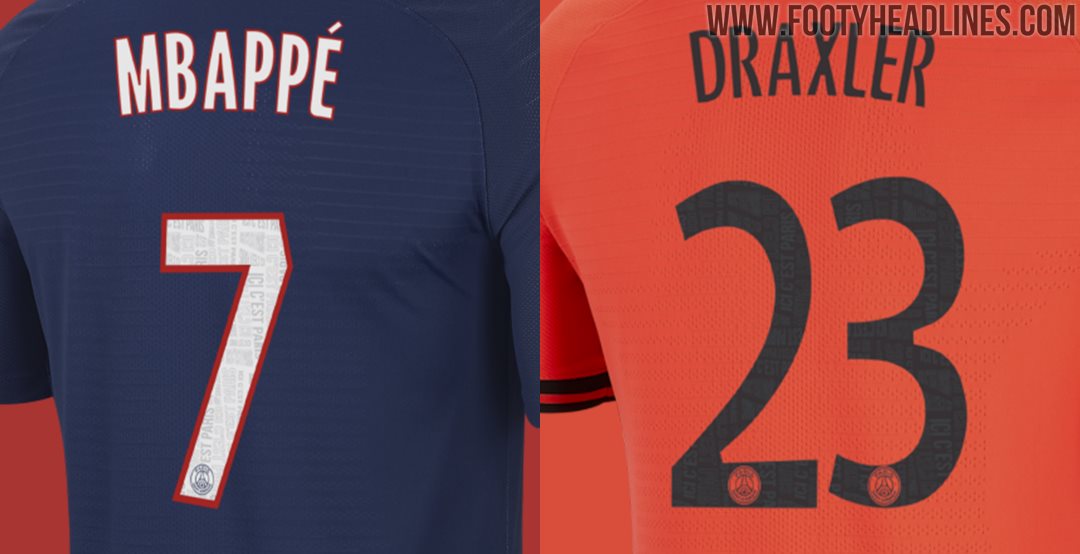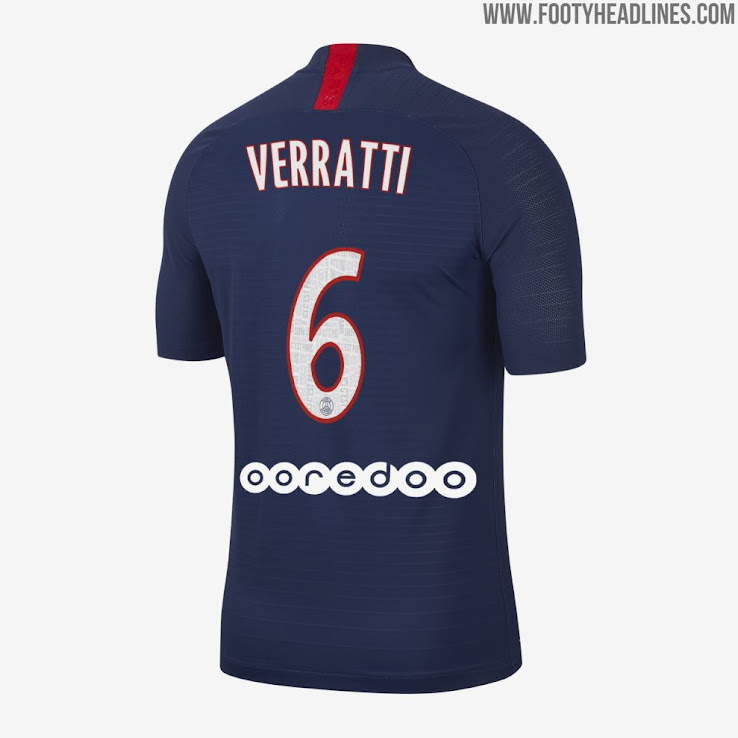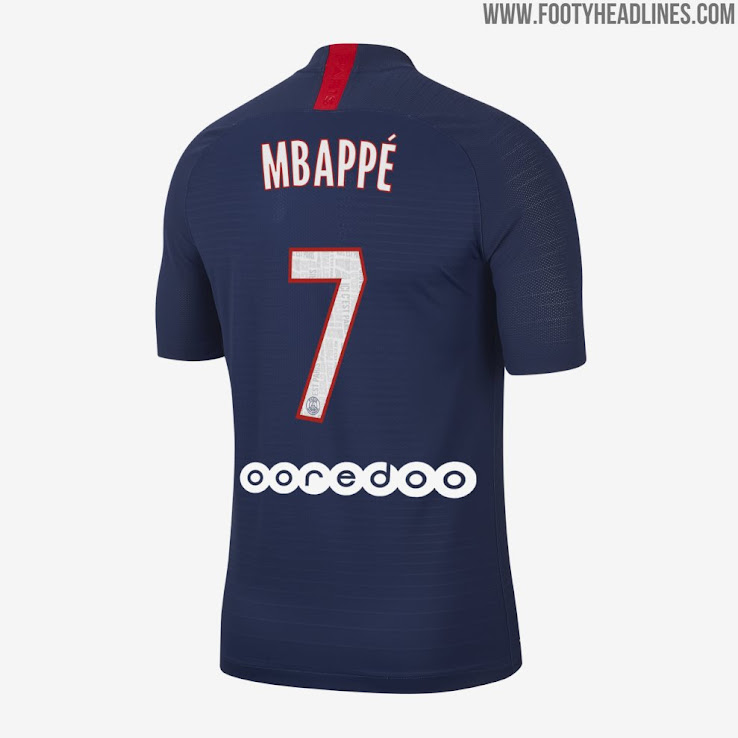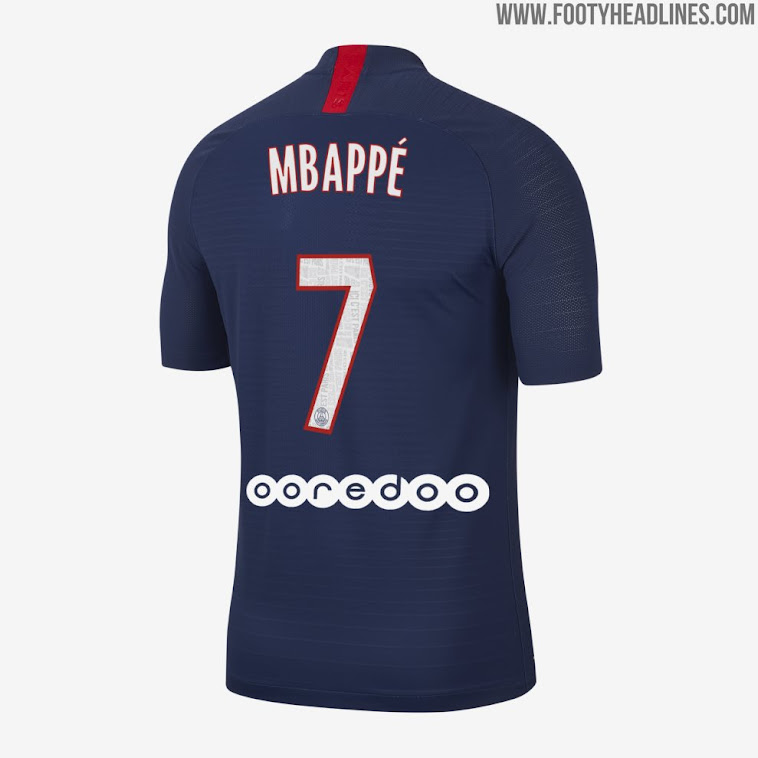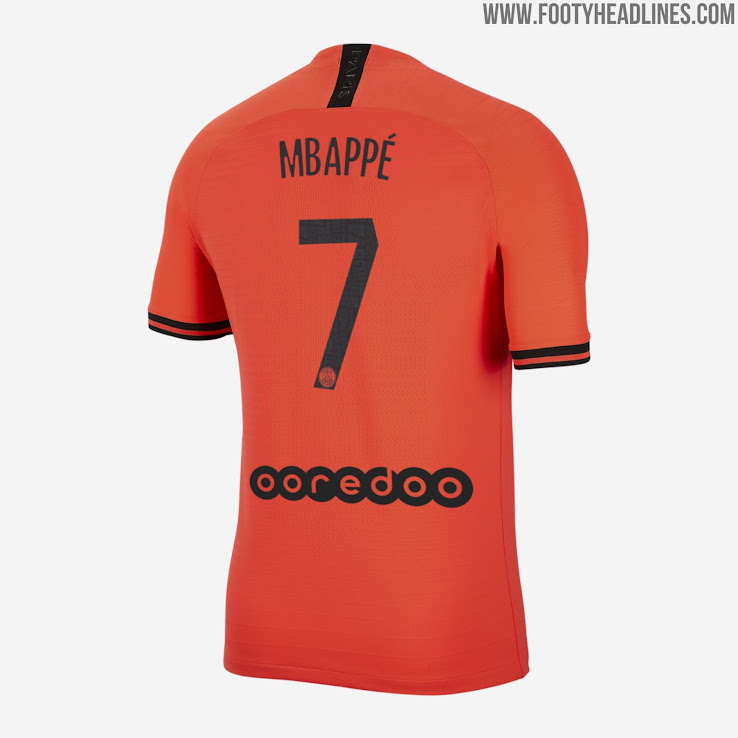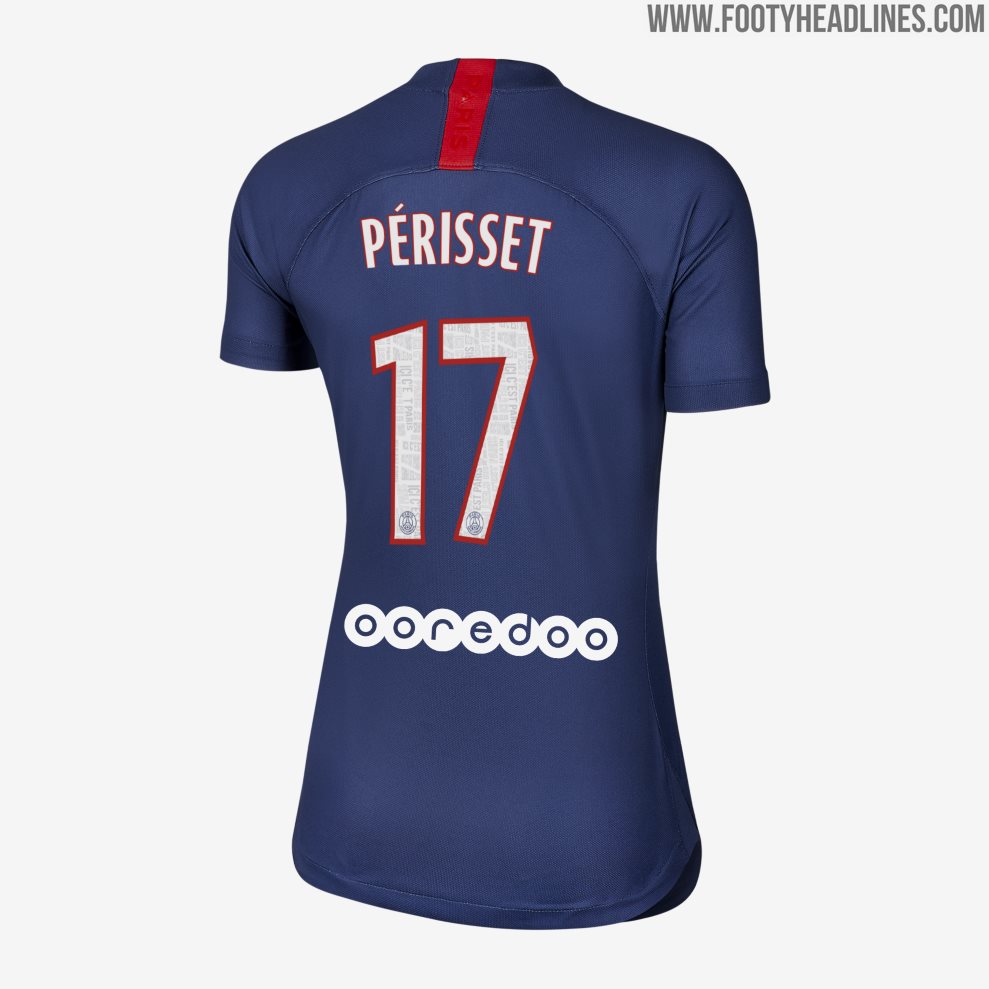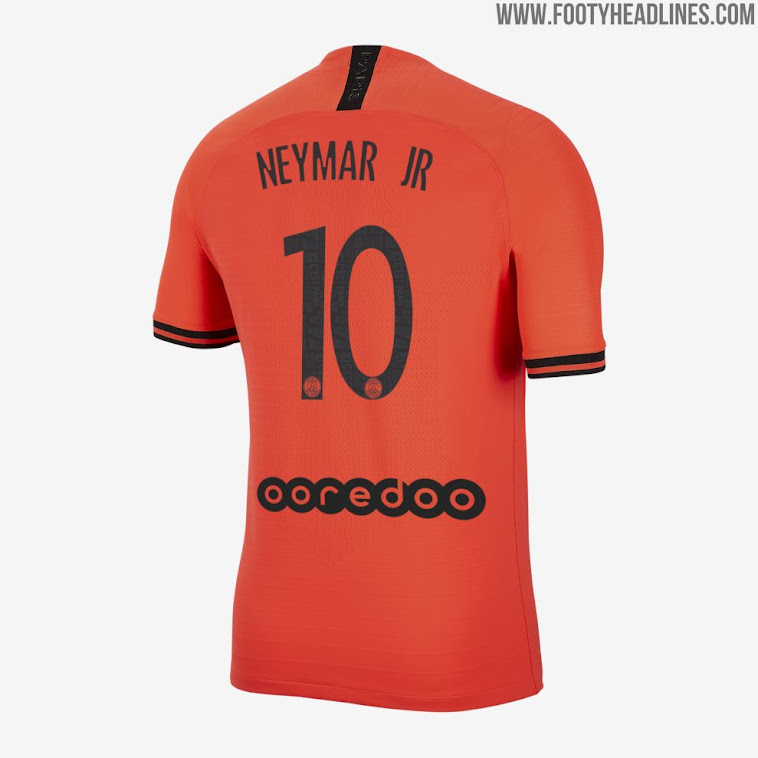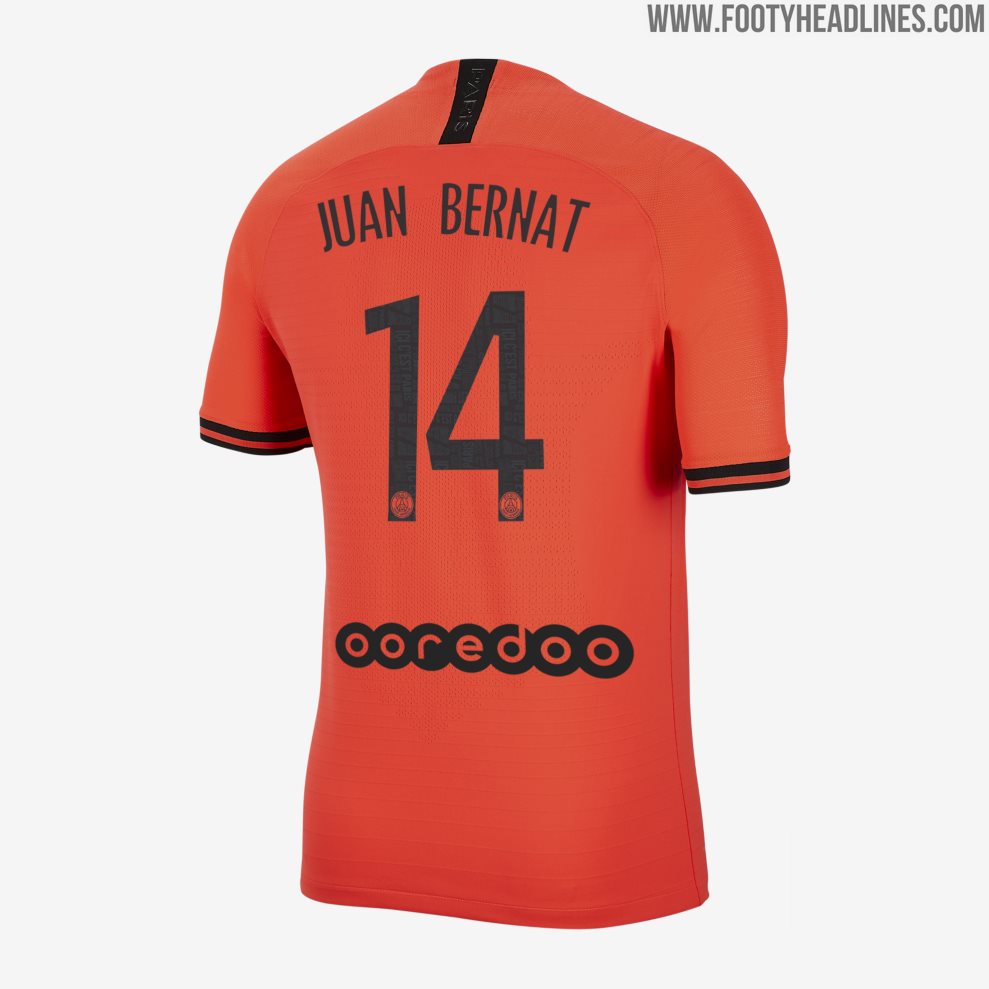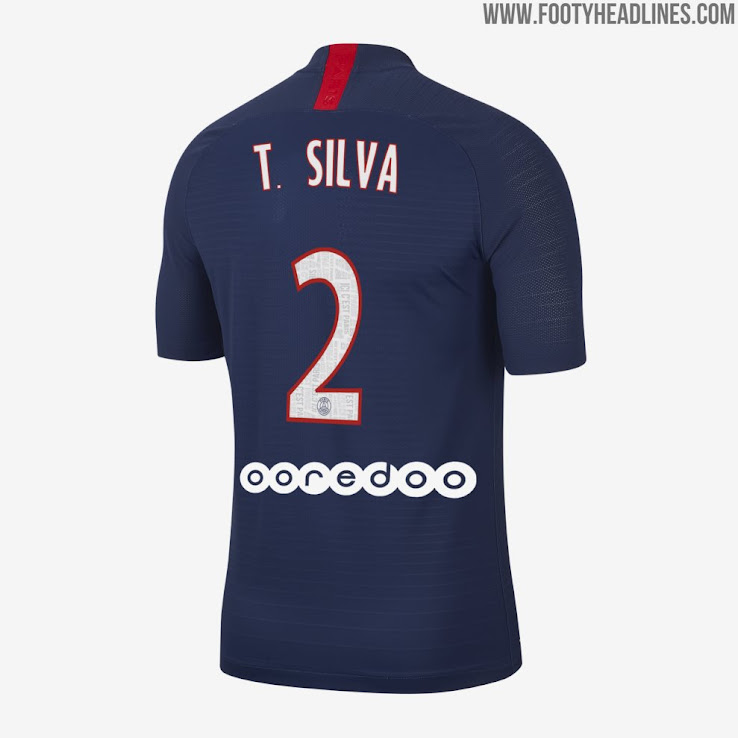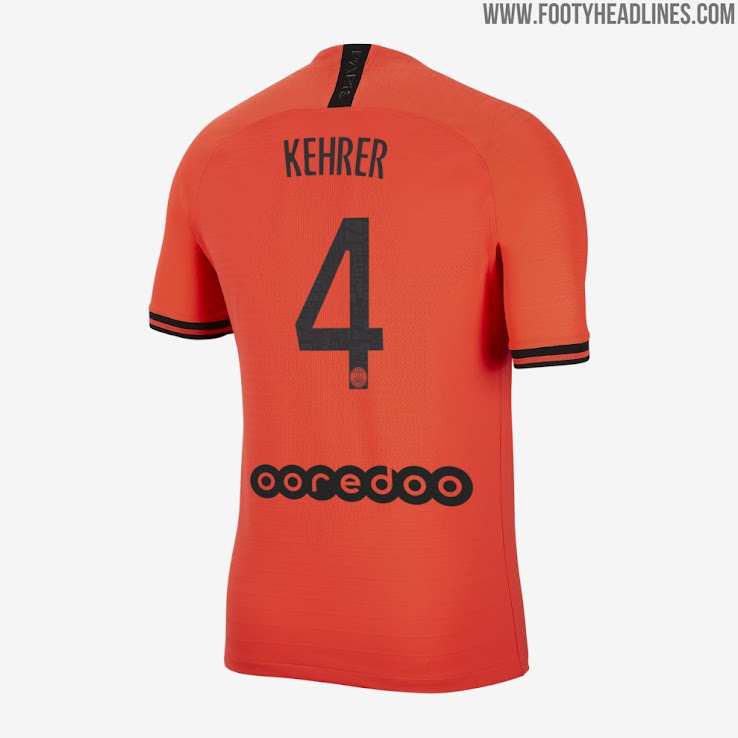
Einzigartige Nike PSG 19-20 Champions League Trikot-Schriftart Enthüllt
Vor einigen Tagen haben wir uns die maßgeschneiderte Ligue 1 Schriftart von PSG in der Saison 2019/2020 genauer angesehen. Jetzt haben wir weitere Untersuchungen zur PSG 2019-2020 Trikot-Schriftart durchgeführt - es scheint, dass Nike für PSG eine maßgeschneiderte Schriftart für die Champions League (und andere nicht in der Liga organisierte Wettbewerbe) entworfen hat.
Interessanterweise ist vor einigen Monaten eine spezielle Jordan x PSG 19-20 Auswärtstrikot-Schriftart geleaked worden. Es bleibt abzuwarten, ob diese Schriftart jemals veröffentlicht wird - Nike verkauft die in diesem Artikel vorgestellte maßgeschneiderte Schriftart nur auf ihrer Website.
Nike PSG 2019-2020 Trikot-Schriftart
Die Nike PSG 19-20 Trikot-Schriftart bieten einen außergewöhnlichen Look und spielt mit Kanten und Rundungen für einen "freudigen Look". Am unteren Ende befindet sich eine einfarbige Version des PSG-Wappens.
Die Schriftart des Heimtrikots ist weiß mit einem roten Rand, während die Schriftart des Jordan PSG Auswärtstrikots schwarz ohne Rand ist.
Wie die benutzerdefinierte PSG Ligue 1 Schriftart. Die Nike PSG 19-20 Schriftart verfügt über eine subtile Textgrafik mit dem Vereinsmotto "Ici c'est Paris" (Dies ist Paris).